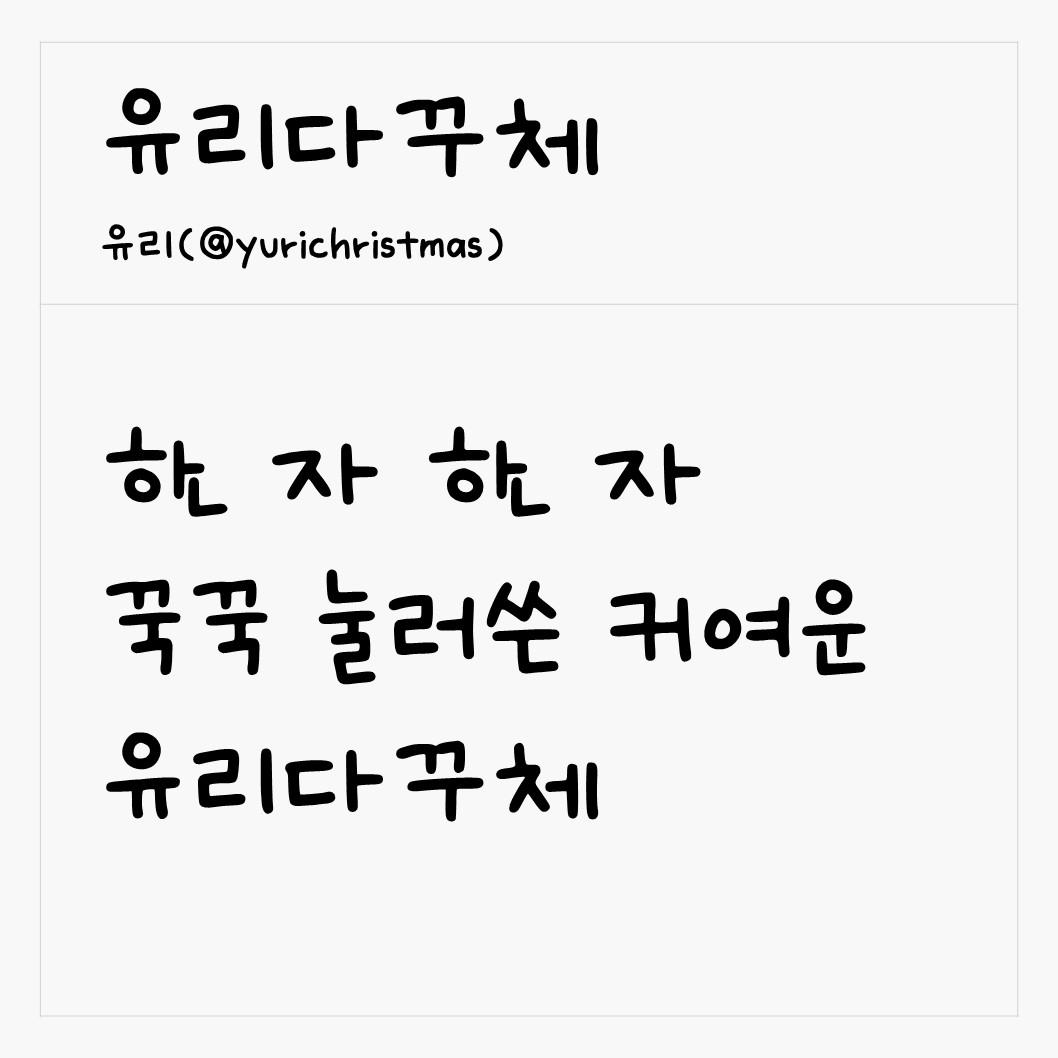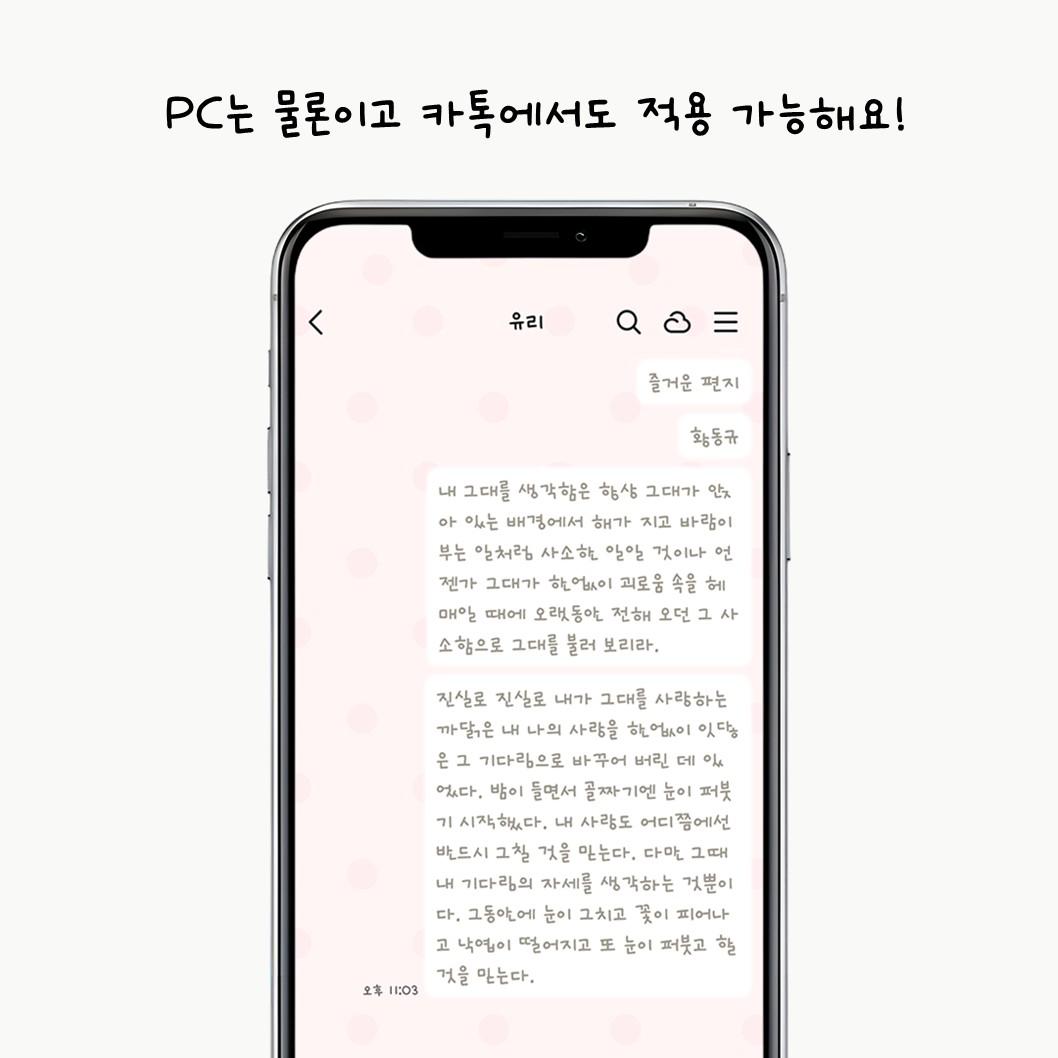
그리운 유리 다꾸체
Griun Yuri Daggu
그리운 유리 다꾸체 소개
올해로 벌써 다꾸 7년차, 많은 분들이 다이어리 속 제 손글씨를 좋아해 주셔서 그 매력을 나누고 싶은 마음으로 폰트를 만들게 되었어요. 유리다꾸체는 제가 평소에 다꾸를 할 때처럼 한 자 한 자 꾹꾹 눌러 쓰는 손맛을 그대로 담아낸 손글씨 폰트예요. 나만의 속도로 눌러 쓴 글씨가 가진 소박하지만 특별한 매력. 일상에 작은 ‘다꾸 감성’을 더하고 싶을 때, 유리다꾸체가 함께할게요.